5 Rekomendasi Font untuk CV Karyawan yang Profesional
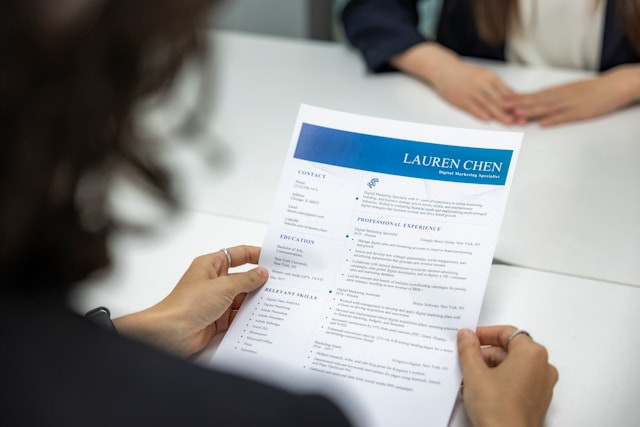
Membuat CV adalah hal yang wajib dilakukan oleh calon karyawan sebelum melamar pekerjaan. Membuat CV tidak boleh dilakukan dengan asal-asalan. Selain memerhatikan informasi data diri, calon karyawan juga perlu memilih font untuk CV.
Memilih font CV adalah hal yang krusial. Hal itu karena tidak semua font tulisan cocok untuk CV pekerjaan.
Daftar Font untuk CV Agar Terlihat Profesional
Dikutip dari buku Cara Membuat CV ATS Friendly Agar Cepat Mendapat Kerja, Suryanto (2023:96), CV atau Curriculum Vitae adalah sebuah dokumen yang berisi tentang data diri, riwayat pendidikan, pengalaman kerja, dan keterampilan yang dimiliki oleh seseorang yang akan digunakan sebagai bahan pertibangan oleh pihak HRD dalam proses seleksi karyawan.
CV adalah kesan pertama yang akan dilihat oleh HRD. Dengan CV yang baik, peluang kandidat untuk dihubungi oleh HRD semakin tinggi. Oleh karena itu, membuat CV tidak boleh dilakukan dengan asal.
CV harus dibuat sesuai dengan data diri dan pengalaman. Selain itu, calon karyawan juga perlu memperhatikan format hingga font untuk CV.
Font yang tepat dapat membuat CV terlihat lebih rapi dan mudah untuk dibaca. Adapun rekomendasi font yang cocok untuk CV sebagai berikut.
1. Calibri
Calibri adalah font yang saat ini banyak digunakan untuk tulisan. Calibri merupakan font default di Microsoft Word. Calibri menjadi salah satu font favorit karena bentuknya yang sederhana dan mudah untuk dibaca.
2. Lato
Rekomendasi kedua adalah Lato. Lato merupakan font yang sebenarnya memang diciptakan untuk memenuhi kebutuhan korporasi. Lato memiliki ciri khas gaya yang formal. Sehingga cocok untuk digunakan saat menulis CV.
3. Helvetica
Salah satu font yang paling terkenal dan banyak digunakan para pekerja di bidang kreatif adalah Helvetica. Helvetica banyak digunakan untuk berbagai keperluan. Salah satunya menulis CV karena desain tulisan yang sederhana dan terlihat profesional.
4. Georgia
Selain Calibri, Georgia dapat dijadikan font pilihan saat membuat CV. Georgia memiliki bagian ekor yang cukup tebal. Hal ini membuat font jenis serif ini nyaman untuk dibaca meskipun dengan ukuran kecil.
5. Tahoma
Terakhir adalah Tahoma. Tahoma adalah font dengan desain yang minimalis. Jika dibandingkan dengan jenis font lain, jarak antar huruf Tahoma terlihat lebih rapat. Meskipun demikian, Tahoma mudah dibaca sehingga banyak digunakan untuk CV.